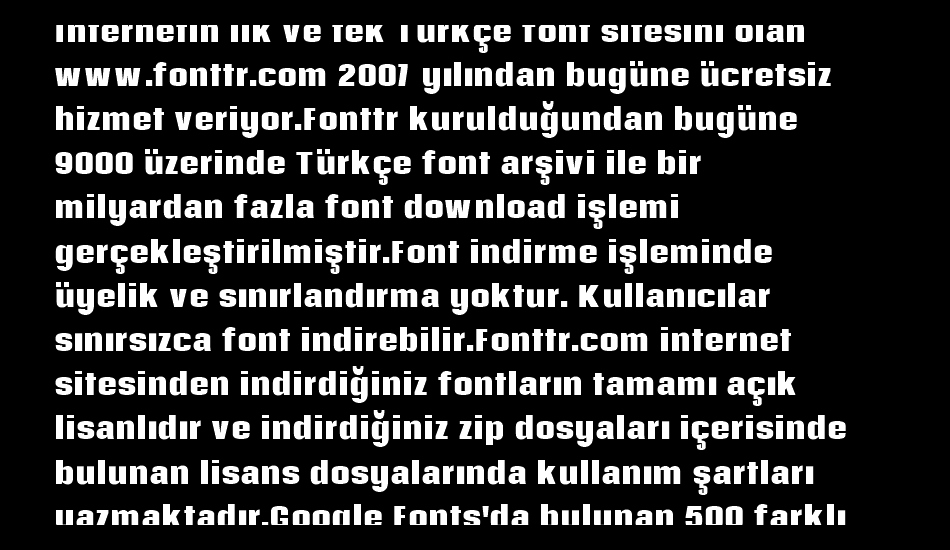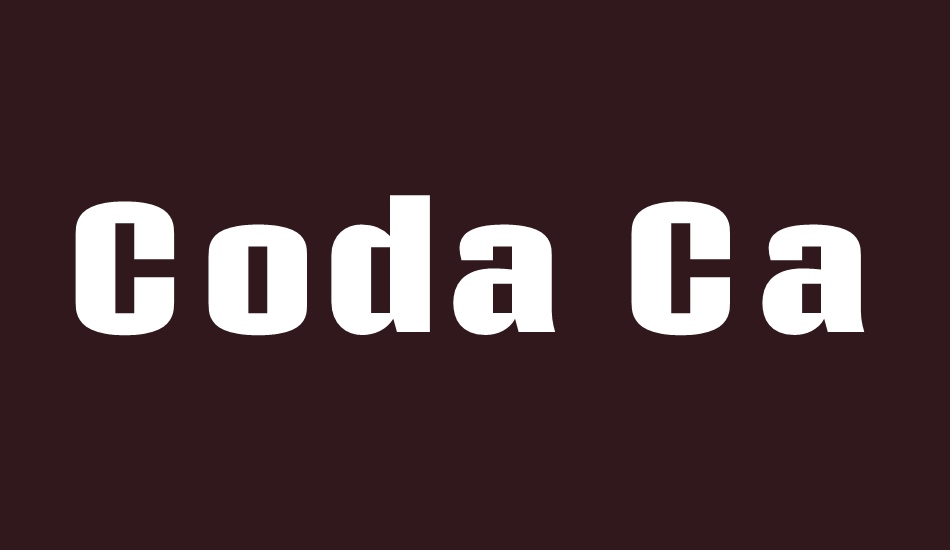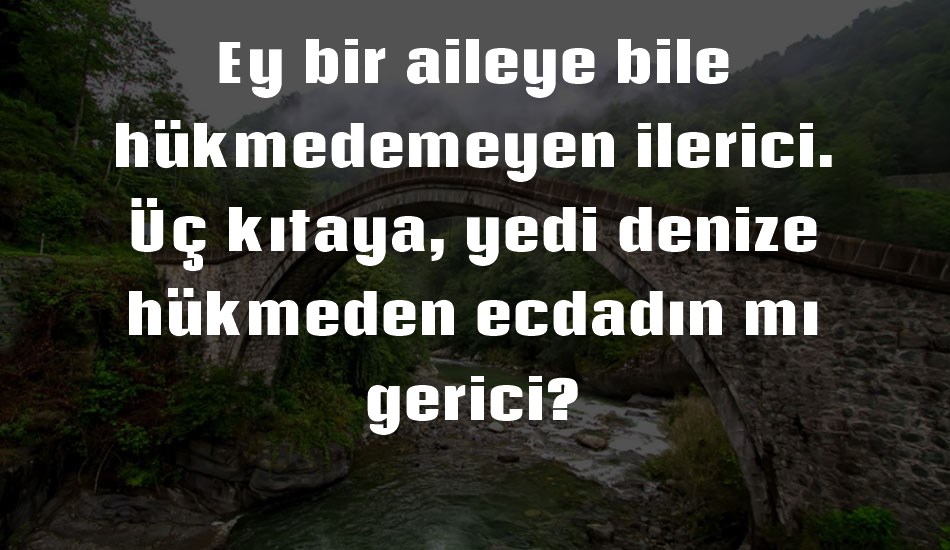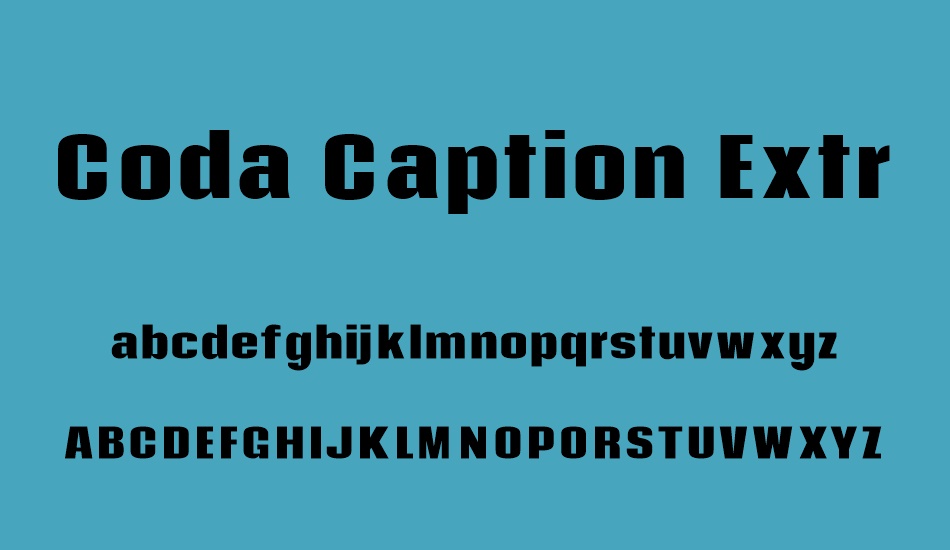
Coda Caption font
Göz alıcı, karışıklık yaratmayan, bant genişliği tasarrufu sağlayan Coda, dünya çapında web için mütevazi, pratik, etkili bir ağır görüntü fontu olarak tasarlanmıştır. Web sayfalarına cesur bilgi getirmek için büyük boylarda kullanılmak üzere tasarlandı.
Coda Caption ExtraBold font